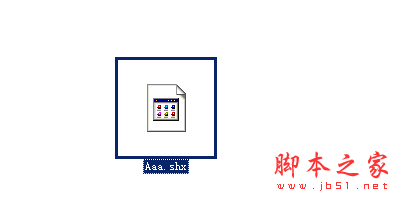
aaa.shx字體是一款可以在autocad軟件中運(yùn)行使用的cad字體,也是autocad軟件中最常用的一款大字體,單線簡體中文字體,支持全角的標(biāo)點(diǎn)符號,是建筑專業(yè)設(shè)計(jì)人員的必備字體,因?yàn)檐浖姹镜牟灰恢?,可能?huì)導(dǎo)致某些版本的aaa.shx字體缺失。本站提供了aaa.shx字體免費(fèi)下載地址,有需要的朋友們千萬不要錯(cuò)過。